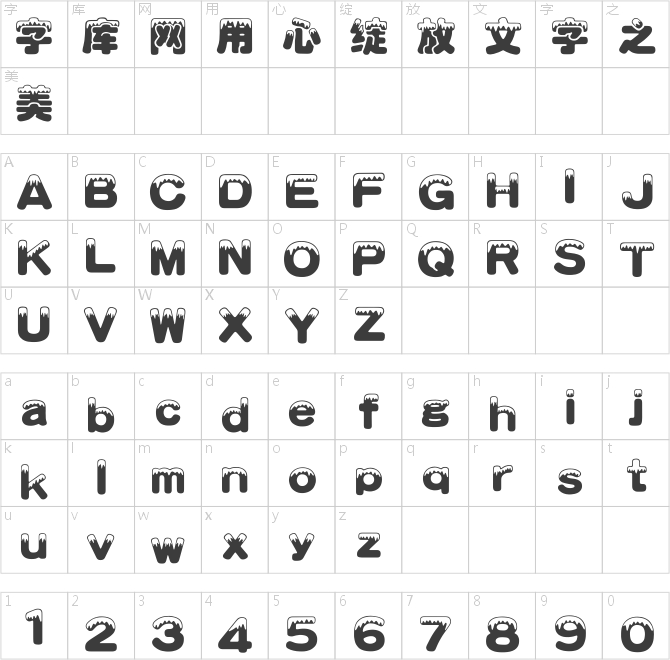
字體名稱(chēng): 漢儀雪峰體W
漢儀雪峰體W
漢儀雪峰體W介紹
漢儀雪峰體W字體漢儀雪峰體簡(jiǎn)繁字庫(kù)是一款讓人賞心悅目、百看不厭的中文字體,適合各類(lèi)廣告和產(chǎn)品包裝設(shè)計(jì)應(yīng)用,字體大小8.95MB,格式為ttf字體,上傳用戶(hù)是伊寧,作者/版權(quán)方為漢儀字庫(kù)